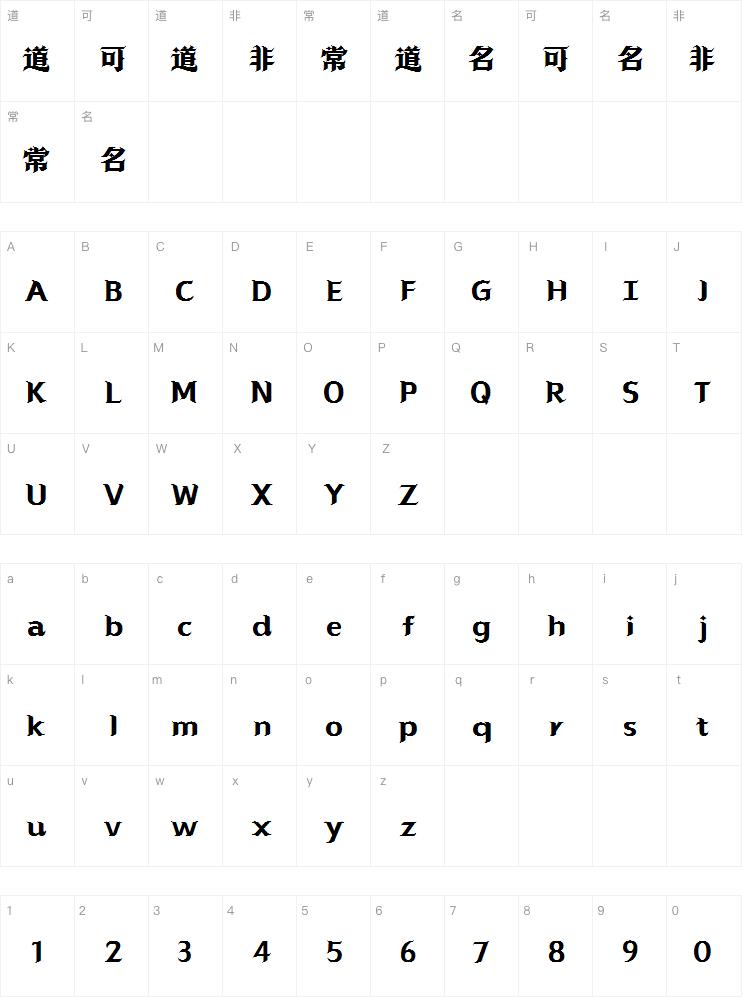
山海星夜哥特,是一款全新的字体,包含汉字9169个,符号200+个。该字体是一款哥特风汉字字体。字体融合了西方哥特元素,字体独特,新颖华丽。这款字体有着很强的装饰性和醒目的视觉效果,字体重心略微偏上、结构空间均衡、字面趋于方形,整体感觉稳重规整。笔画富有棱角。起笔、收笔和转折处都设计成锐利的“尖钩”造型,看起来锋利,攻击性十足,带给人魔幻、暗黑的视觉感受。撇和捺作为字形中延展性最高的两个笔画,形态凌冽十足,富有张力。点笔画形态丰富多样,在表现笔画冷酷、锐利的基础上,根据不同的空间大小有不同的诠释。在体现哥特风格的同时呼应了中文的笔画特征,并在设计上有意改善传统哥特体复杂难辨认的特性,尽量做到易辩、易读,保证了字体的实用性。汉字艺术与西方文字的融合,如夜空中闪烁着暗黑光芒,又宛如梵高的《星月夜》般神秘梦幻;个性鲜明的字体特征,散发着神秘而高冷的气息。在华丽而不失婉约中,感受哥特风的魅力。